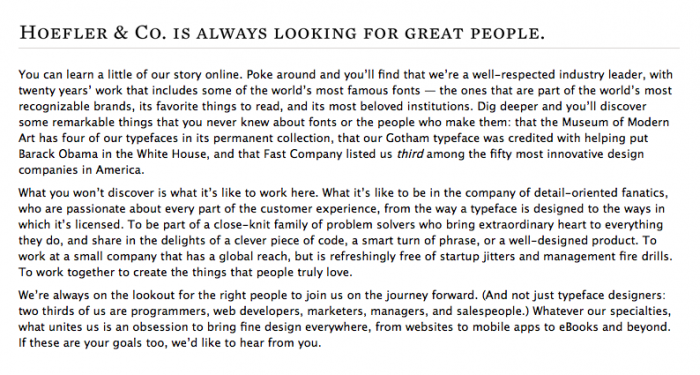
Frere-Jones verklagt Hoefler
Das hätte mich jetzt aber auch gewundert. Nach vorne zu schauen und neu durchzustarten ist sicherlich das Beste, was er tun kann. Ich wünsche ihm viel Glück und Erfolg dabei.  :-)
Die Gestaltung der Website überrascht mich viel mehr. Georgia und Helvetica?! Da wird doch wohl noch was tun, hoffe ich!
Ich sehe Interstate und Benton Modern, beides Fonts von Frere-Jones die über Fontbureau vertrieben werden.
Das liest sich auf der neuen Hoefler-Website – mit all dem Hintergrundwissen – dann auch nicht mehr so einladend: